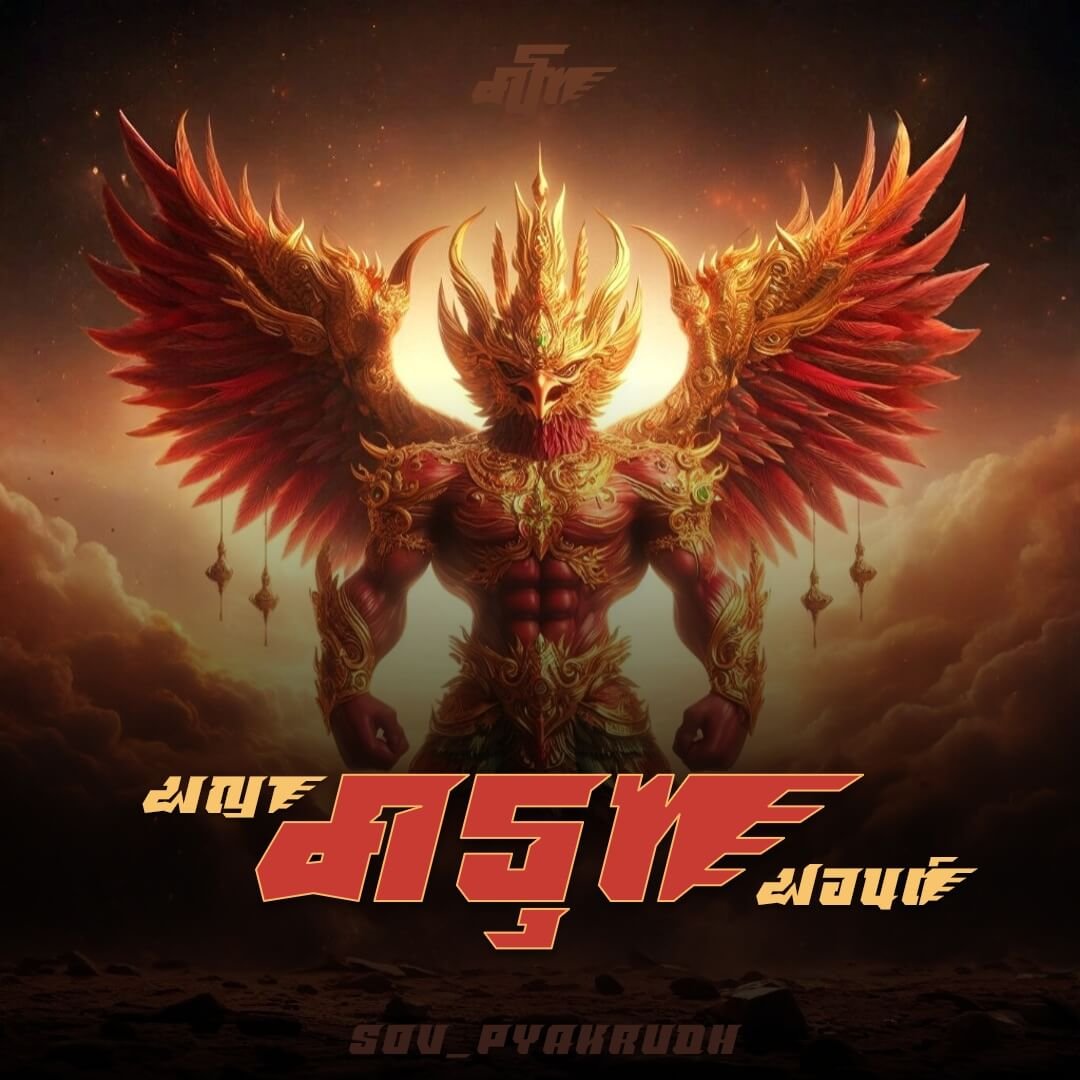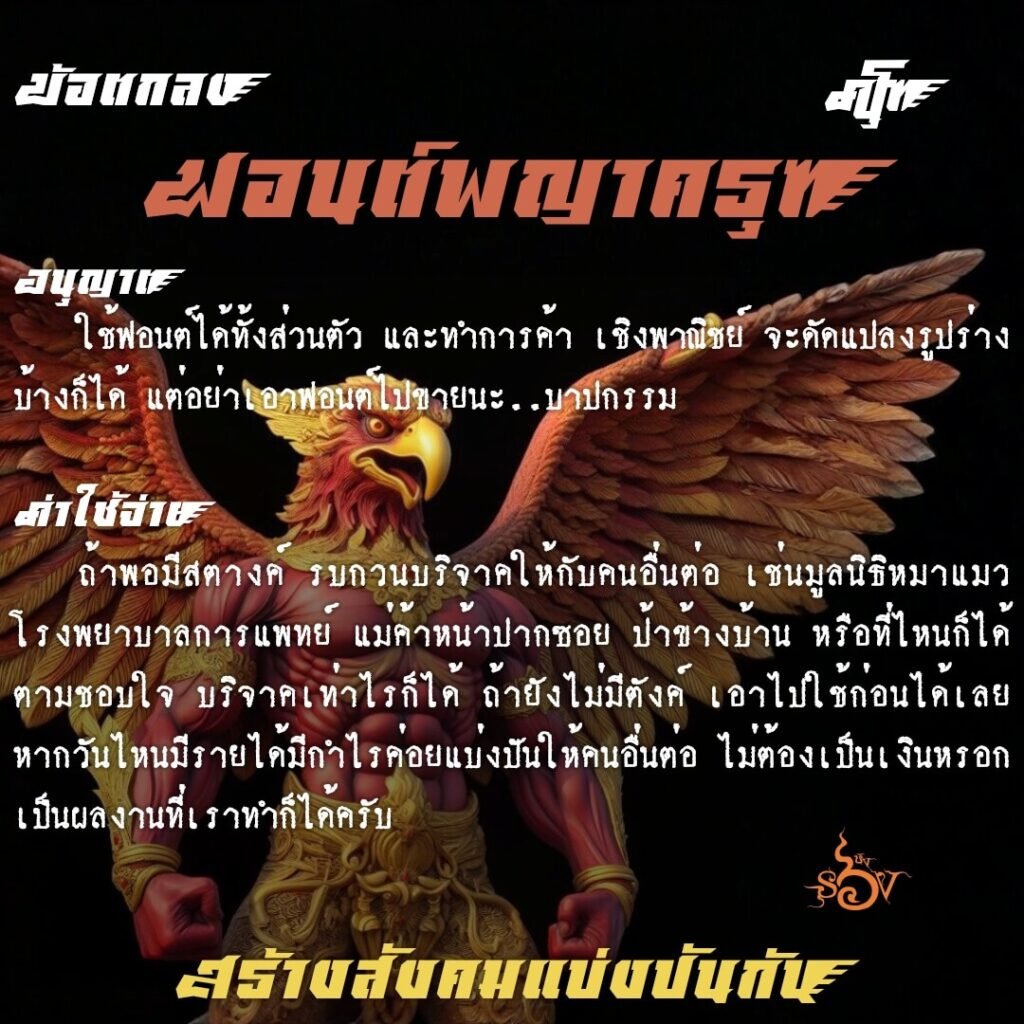
Posted inUncategorized พญาครุฑ (SOV_PyaKrudh) April 3, 2025 พญาครุฑ (SOV_PyaKrudh) อักษรฟอนต์พญาครุฑ ใช้รูปแบบฟอนต์ซิ่งเป็นฐาน เพิ่มอักษรตัวแรกเป็นหัวนก และตัวสุดท้ายเพิ่มเส้นความเร็ว เหมาะใช้เป็นพาดหัวคำสั้นๆ เท่านั้นuvSOVเบื้องหลังการออกแบบ : ฟอนต์ พญาครุฑช่องทางติดต่อ : Worawut Thanawatanawanich คลิกดาวน์โหลด Post navigation Previous Post พญานาค (SOV_PyaNakh)Next Postพญายักษ์ (SOV_PyaYaks)